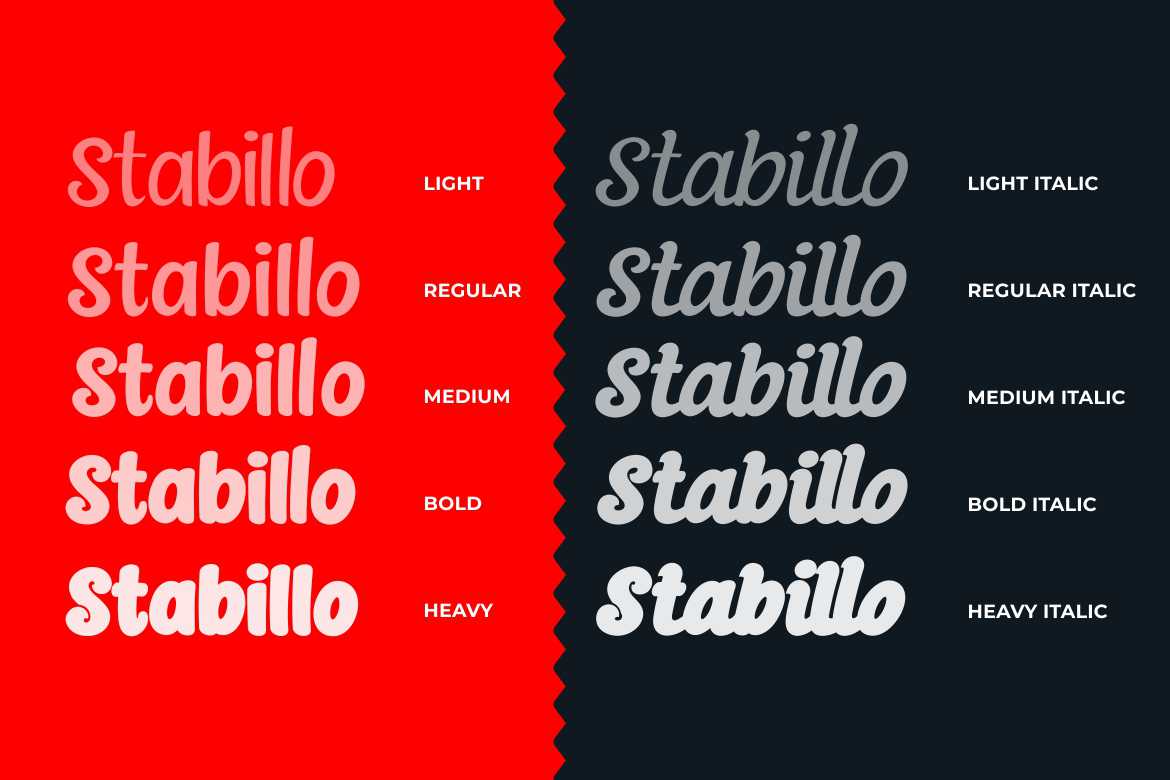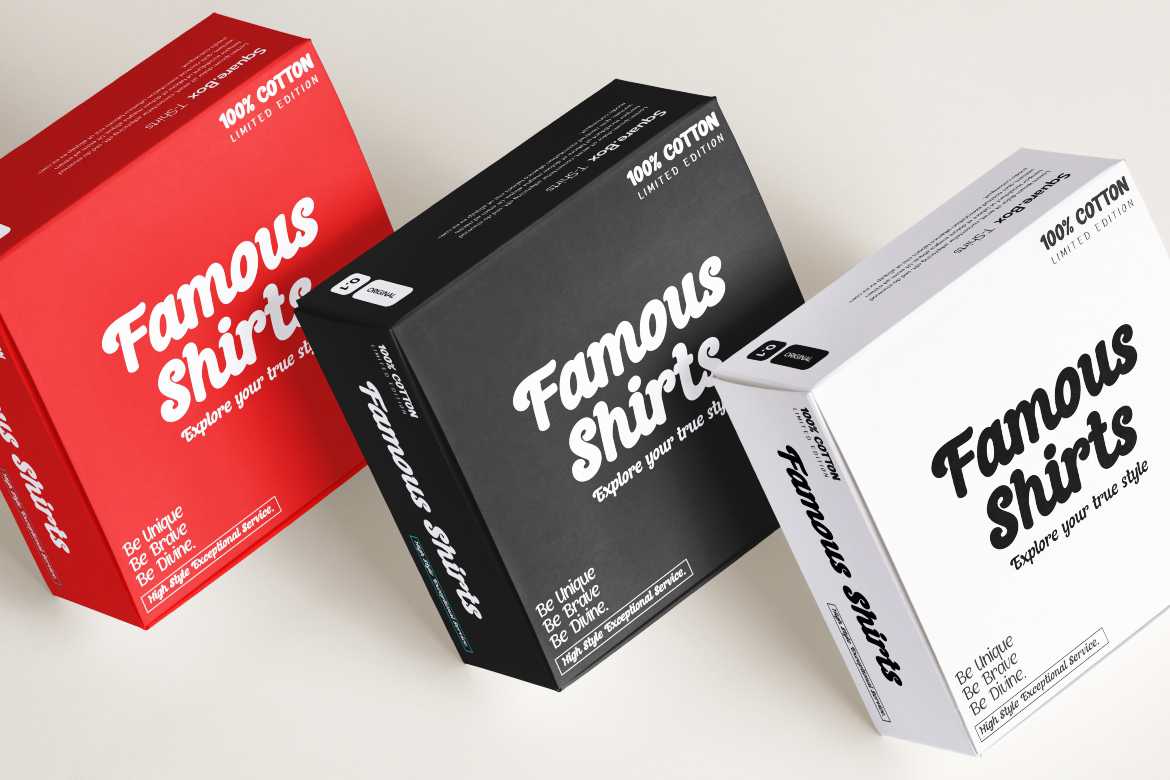
Stabillo Fontfamily是专门为食品和包装设计项目设计的。在该版本中提供了多种替代和校准。由于调色板的10个权重,您可以解决各种专业问题,而无需在其他方的书籍、副标题、,和Main Text。Stabillo FontFamily是专门为食品实体和包装设计项目设计的。在该版本中提供了多种替代和验证。由于调色板的10个权重,您可以解决各种各样的专业问题,而无需花费额外的钱来编辑其他Fonts、字幕和Main Text。